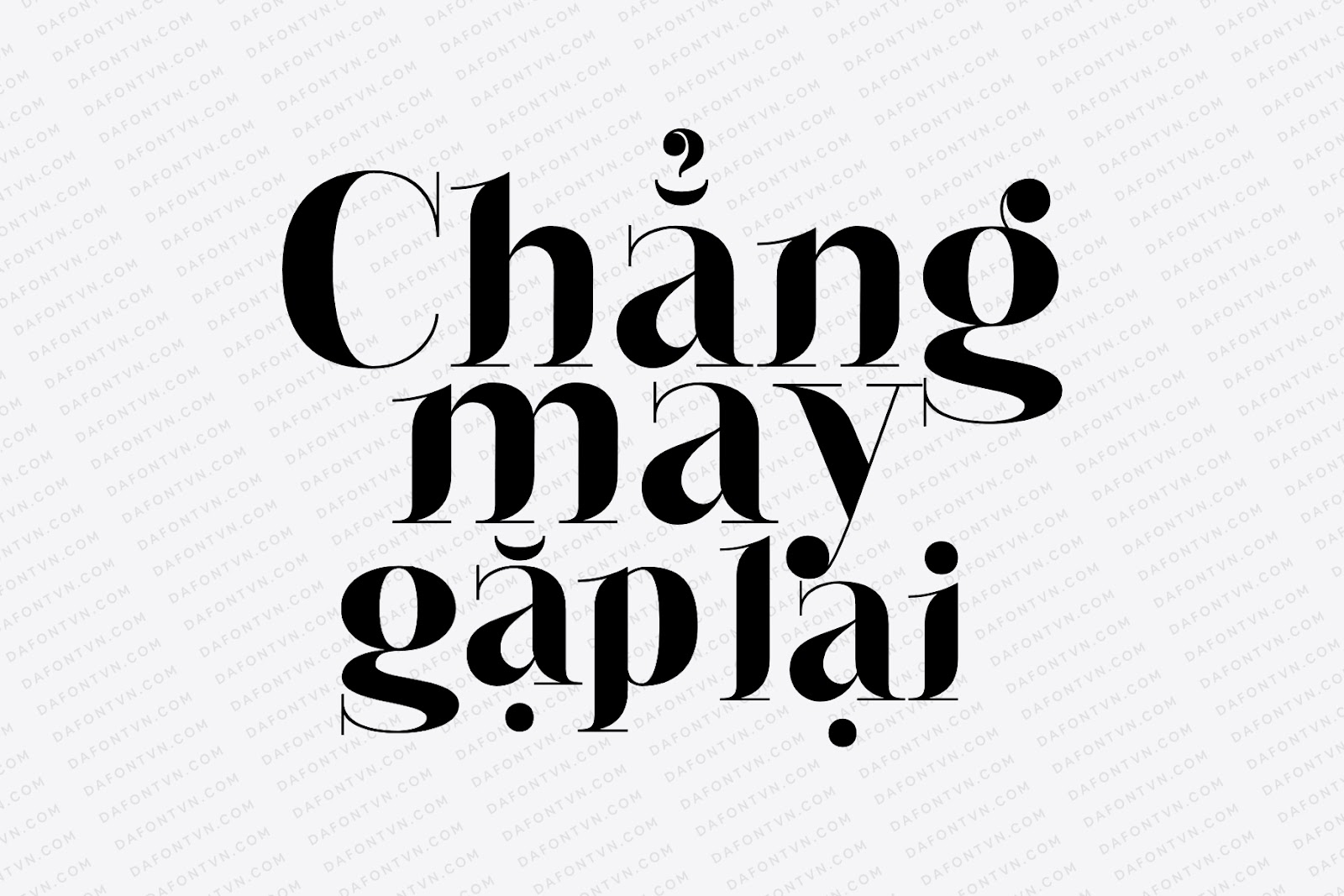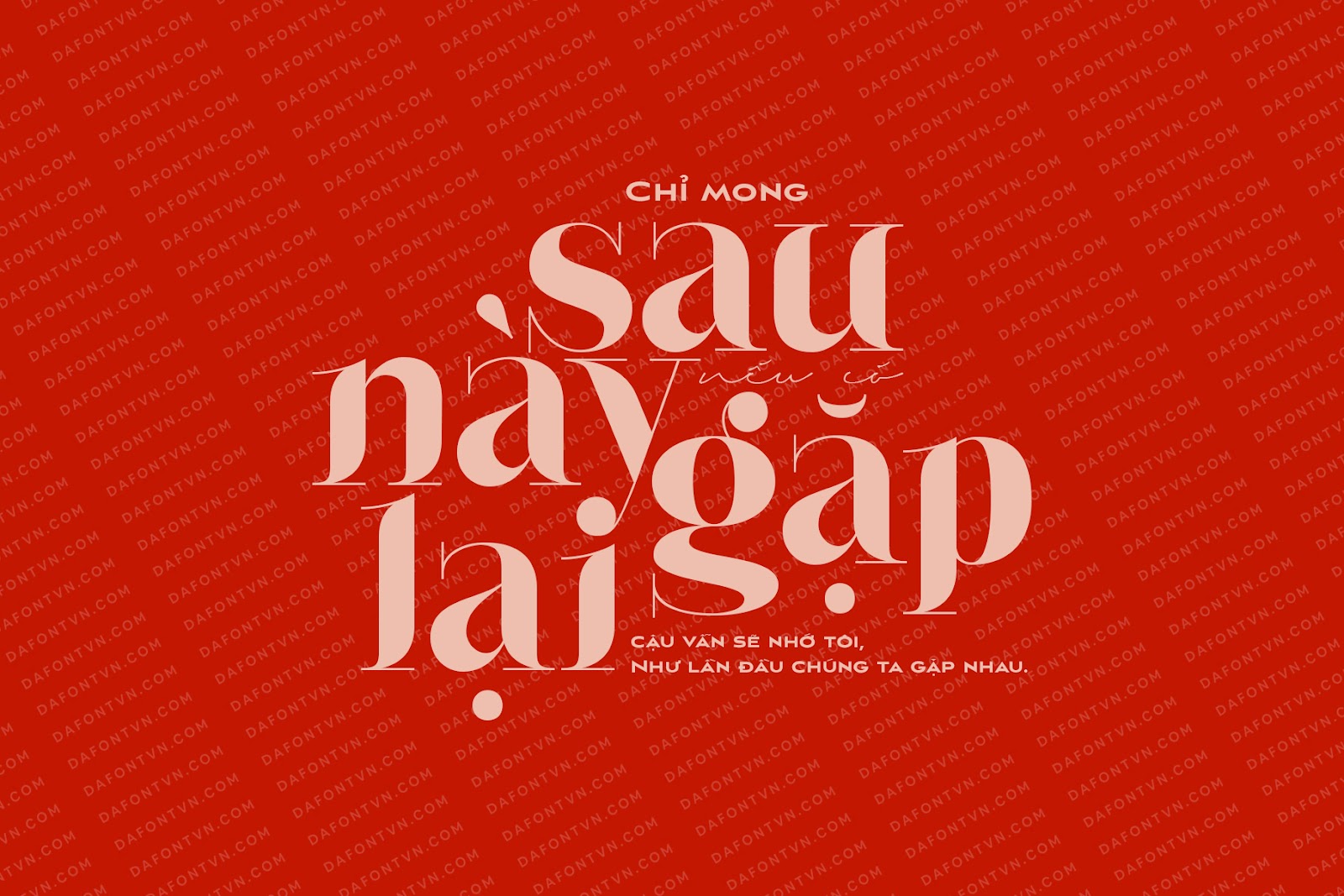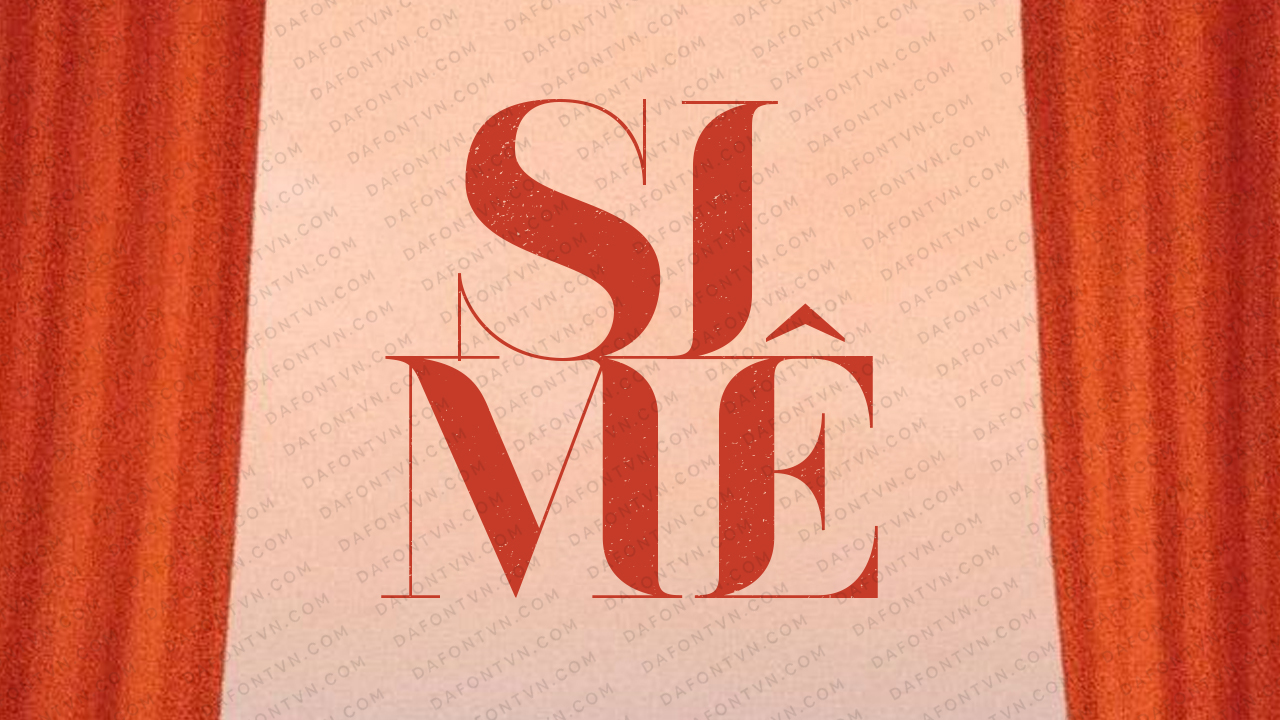
Giới thiệu Ingo Font, một phông chữ hiển thị hiện đại, quyến rũ với độ tương phản cao và những đường nét táo bạo.
Ingo Display với phong cách “deconstructed serif” mang lại cho nó một vẻ ngoài sang trọng, nổi bật và vô cùng ấn tượng. Ingo hoàn hảo cho nhiều thiết kế như tiêu đề, quảng cáo, logo, xây dựng thương hiệu, áp phích, tạp chí, bìa sách…